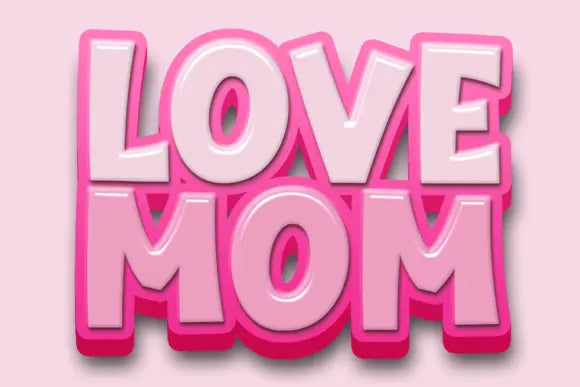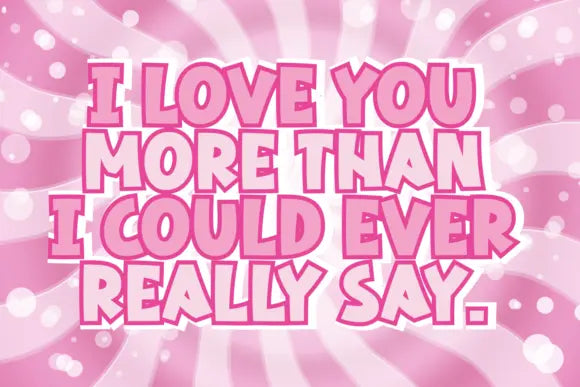
Fuente Pink Squad
Pink Squad es una fuente de visualización linda y encantadora. Caprichosa y un poco peculiar, esta fuente alegrará cada uno de tus diseños.
Agréguelo con confianza a sus proyectos y le encantarán los resultados. Como experto en fuentes profesional, puedo decir con confianza que Pink Squad no es sólo una fuente de exhibición linda y encantadora.
Con su naturaleza caprichosa y peculiar, añade un toque de alegría a cualquier diseño. Incorporar esta fuente a tus proyectos sin duda los potenciará, haciendo que tu trabajo destaque.